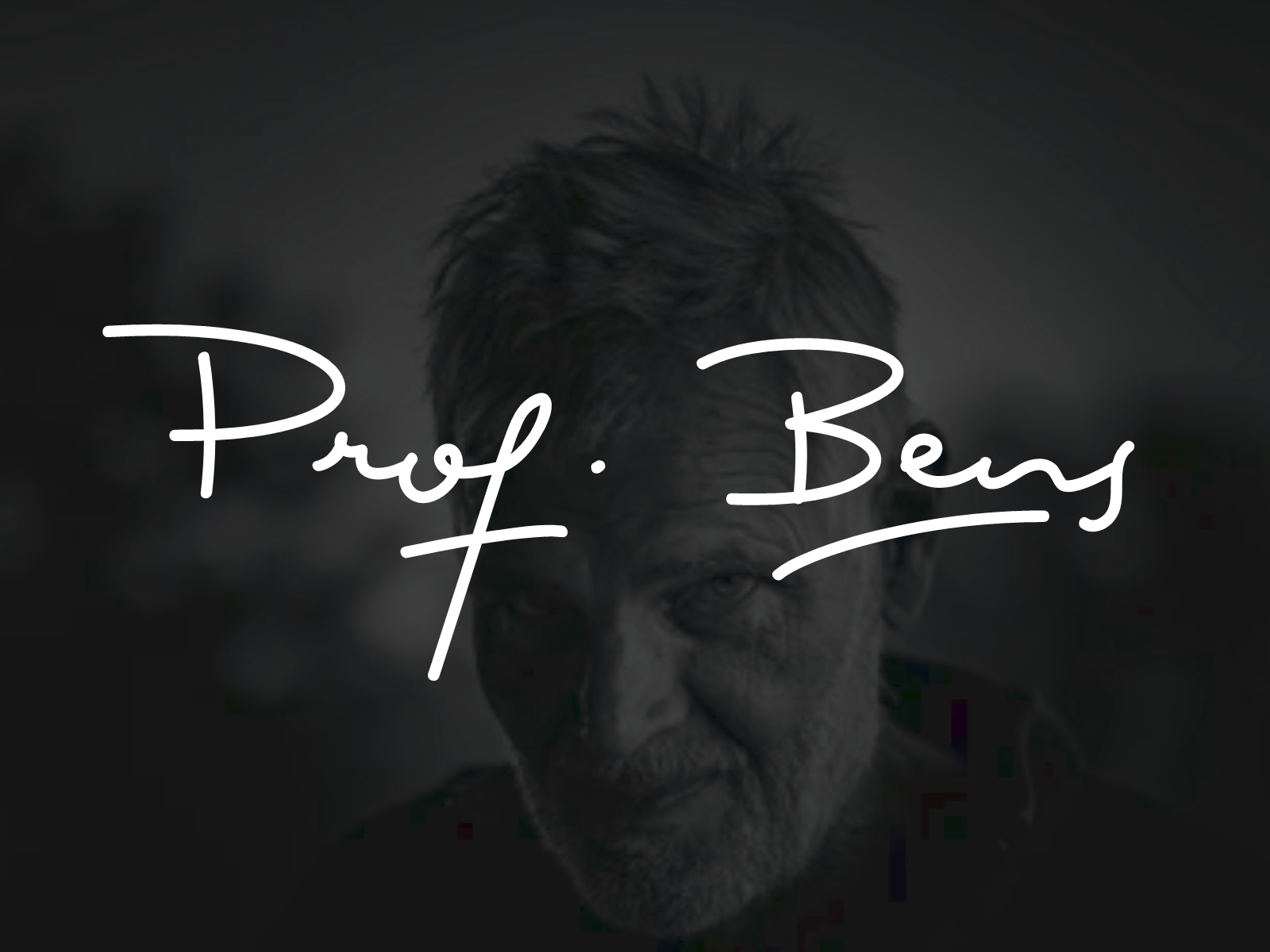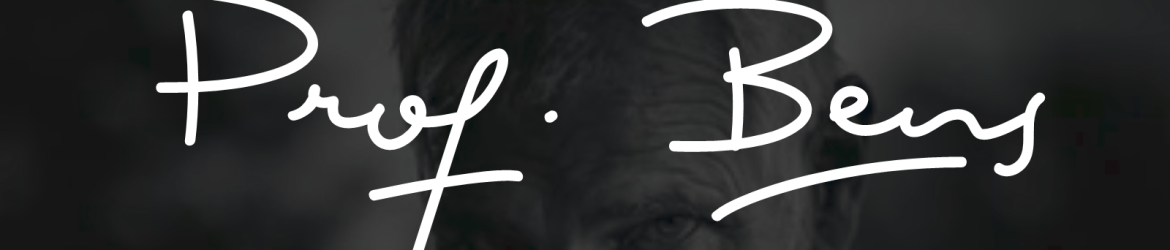
Esta é uma fonte script estilizada e refinada que transmite sabedoria e profissionalismo. Suas alternativas fashionáveis e ligaturas tornam esta font perfeitamente adequada para cada projeto. Ela inclui caracteres e swashes PUA (Unicode Proprietary User Area) codificados, permitindo acesso a todos eles com facilidade. Prof Bens é uma font de escrever cuidadoso que captura o espírito da escrita aquarela em suas linhas sutis e expressivas. As alternativas fashionáveis permitem criar um tom elegante e moderno para qualquer projeto. A inclusão dos swashes PUA na fonte permite acesso às variações de estilo únicas, adicionando profundidade e personalidade ao seu design.